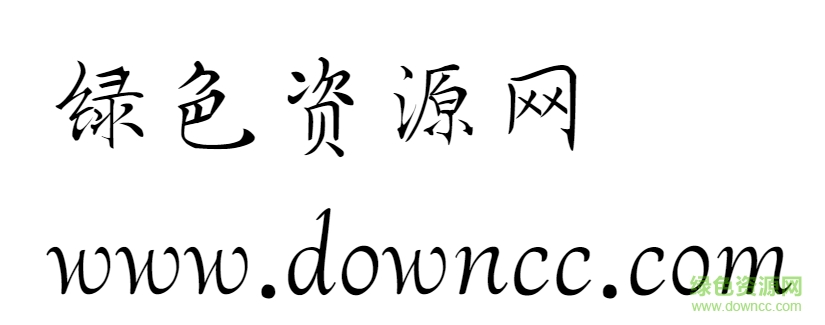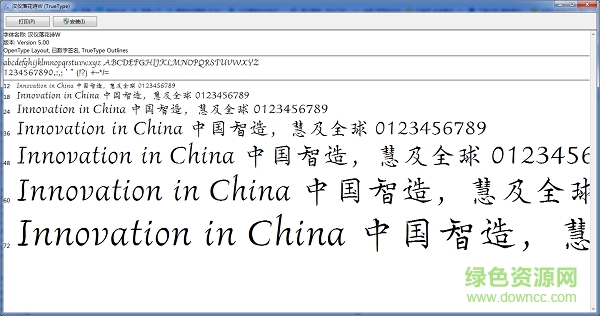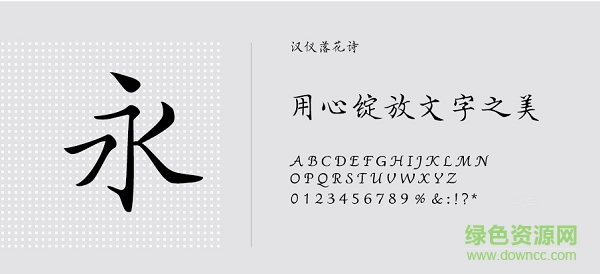
漢儀落花詩w體
漢儀落花詩w字體是一款似花唯美的字體,字體整體線條纖細,落筆柔軟,剛勁之中又帶有一絲絲文藝的氣息,用戶使用此款字體排版能夠使文字看起來更加的柔美,喜歡就來綠色資源網(wǎng)下載吧!
漢儀落花詩w字體簡介:
漢儀落花詩w體是一款來自于明朝唐寅的《落花詩》的行書字體,風(fēng)格復(fù)古的創(chuàng)意字體,筆畫渾然天成,蒼勁有力,十分適用于高端時尚品牌產(chǎn)品的形象設(shè)計和推廣,具有較大范圍的應(yīng)用空間!